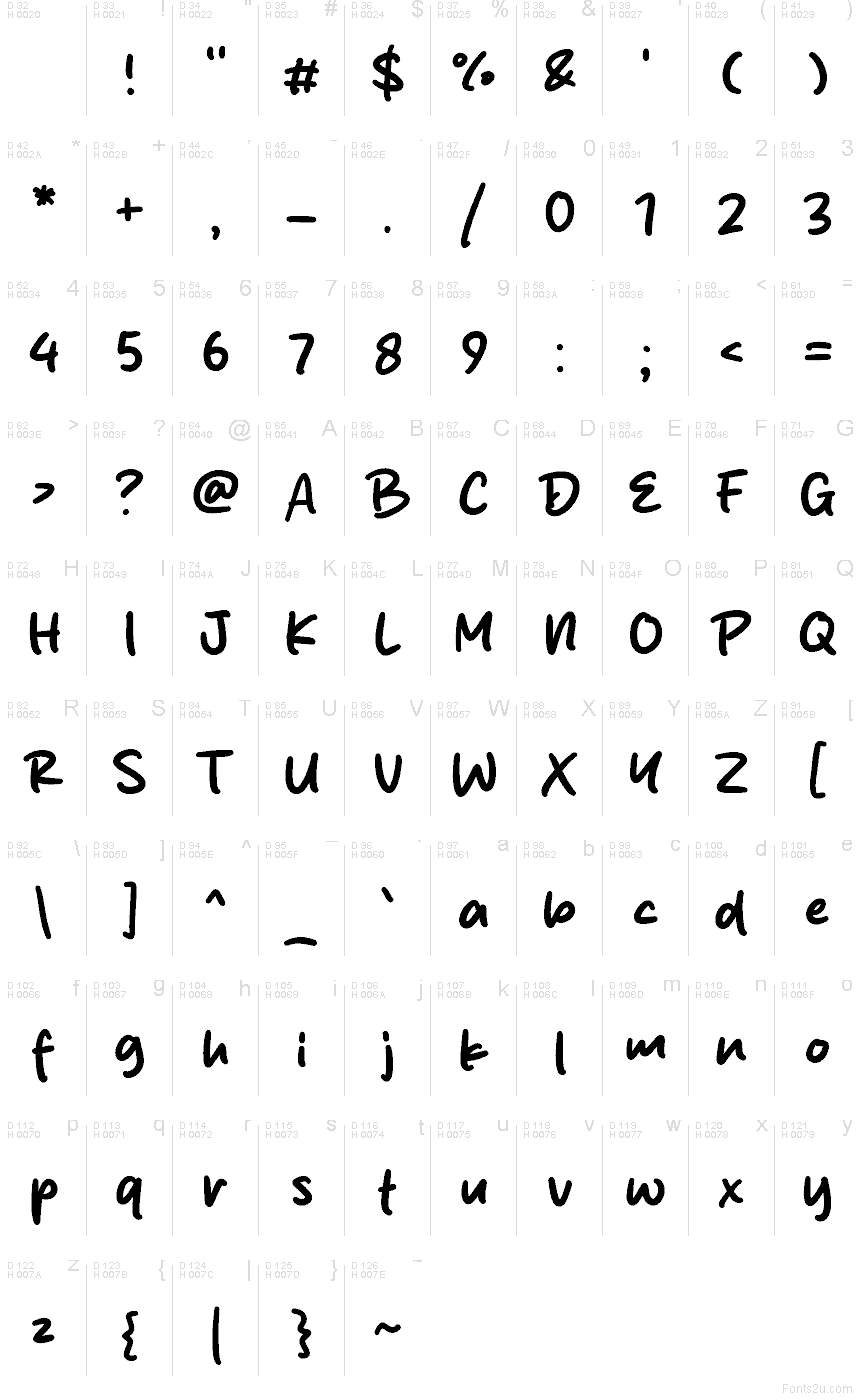
Aulia Callista di MJType è un font gratuito disegnato a mano, che ricorda l'uso di un pennello, dal ritmo casual e vivace. Le lettere sembrano tracciate con un pennarello a punta grossa, con tratti arrotondati, raccordi morbidi e forme leggermente rimbalzanti che conferiscono allo stile un carattere amichevole, lontano da un aspetto troppo formale.
Si adatta perfettamente al packaging, all'identità visiva di caffetterie, grafiche per social media, biglietti d'auguri e titoli di poster dove è richiesto un font gratuito dal tocco personale e immediato. Usalo per titoli brevi, bozzetti di loghi, copertine o branding basato su nomi, quando vuoi che la scrittura mantenga il suo calore, il segno dell'inchiostro e un movimento fluido.